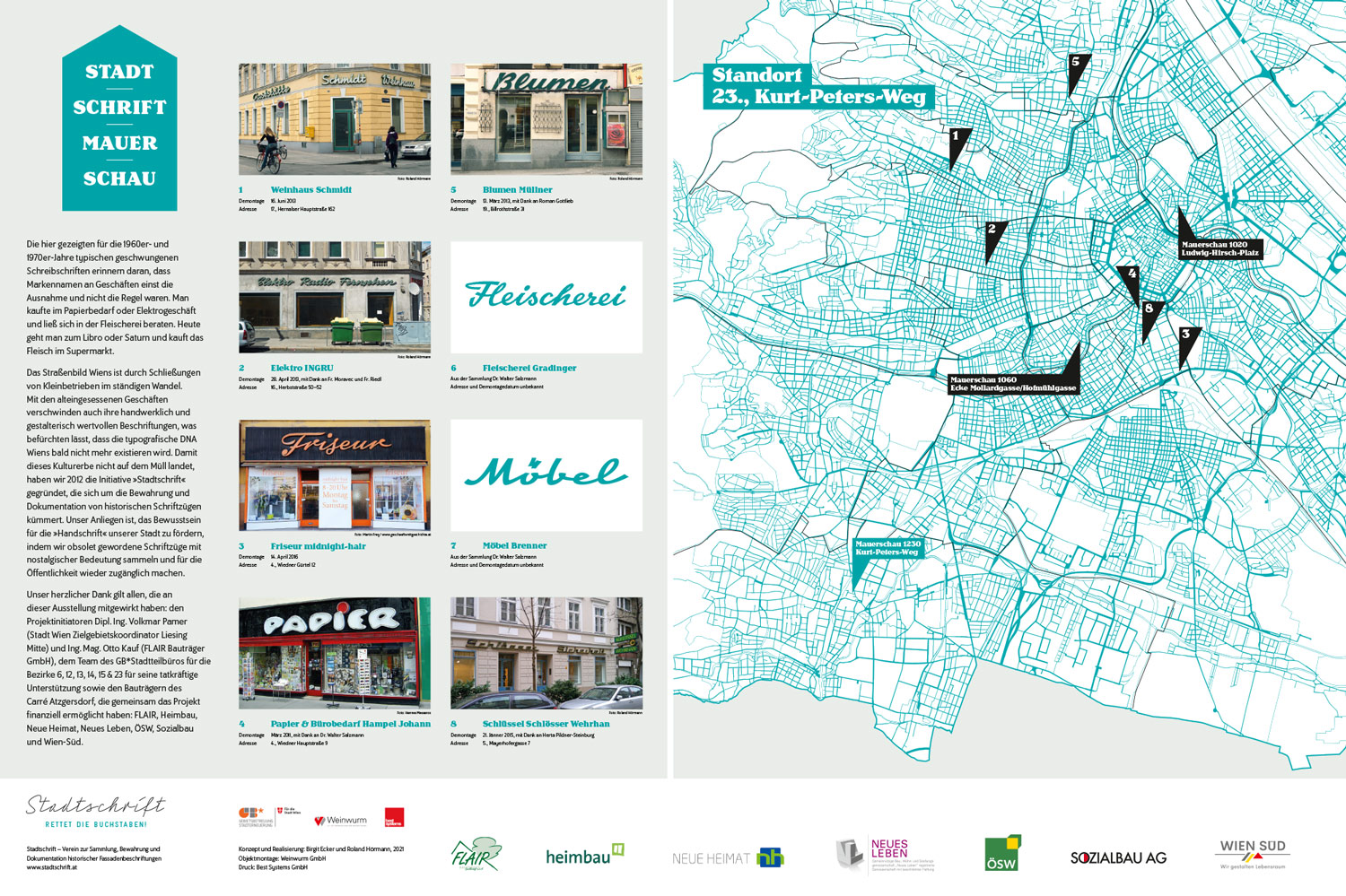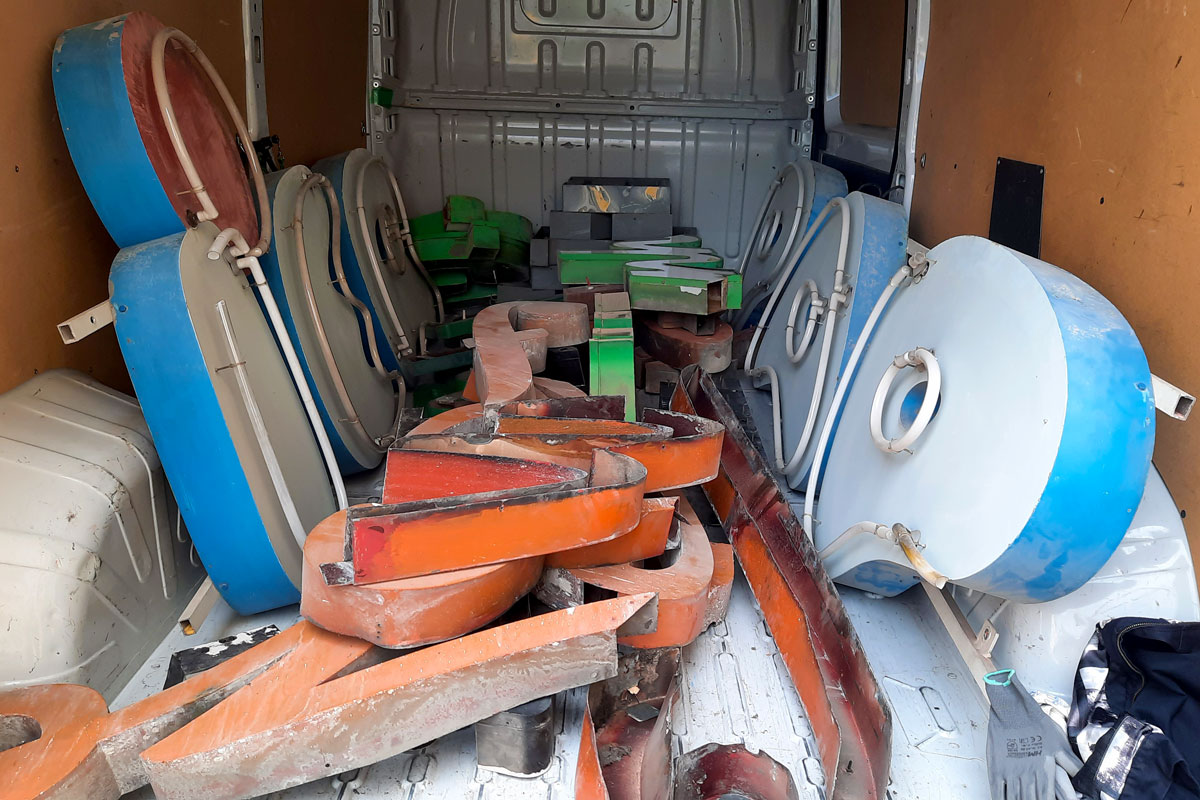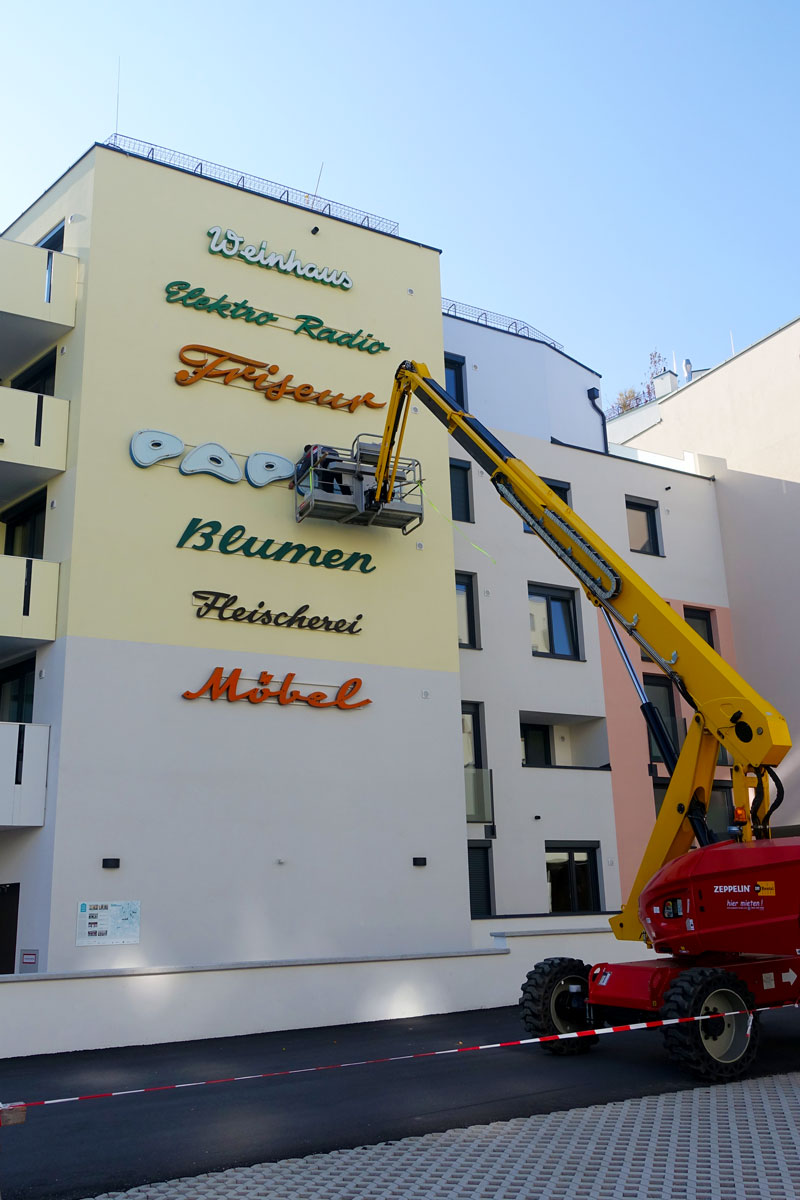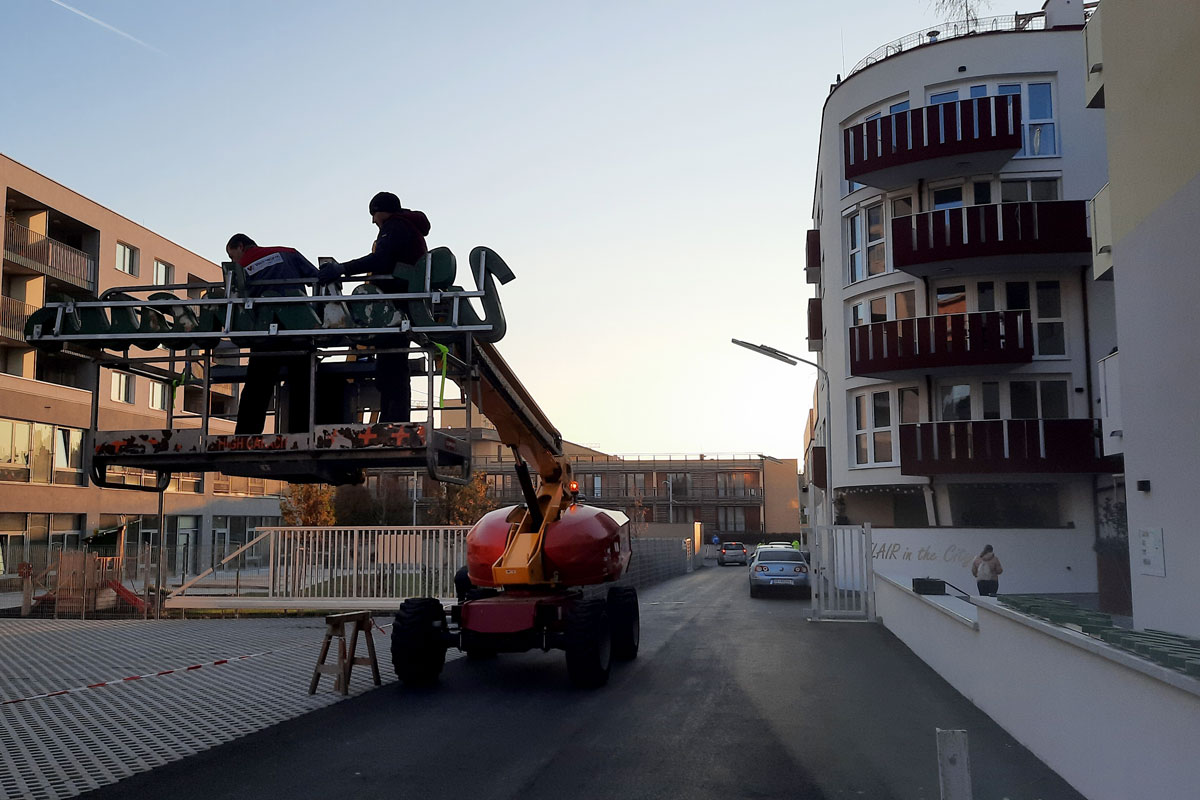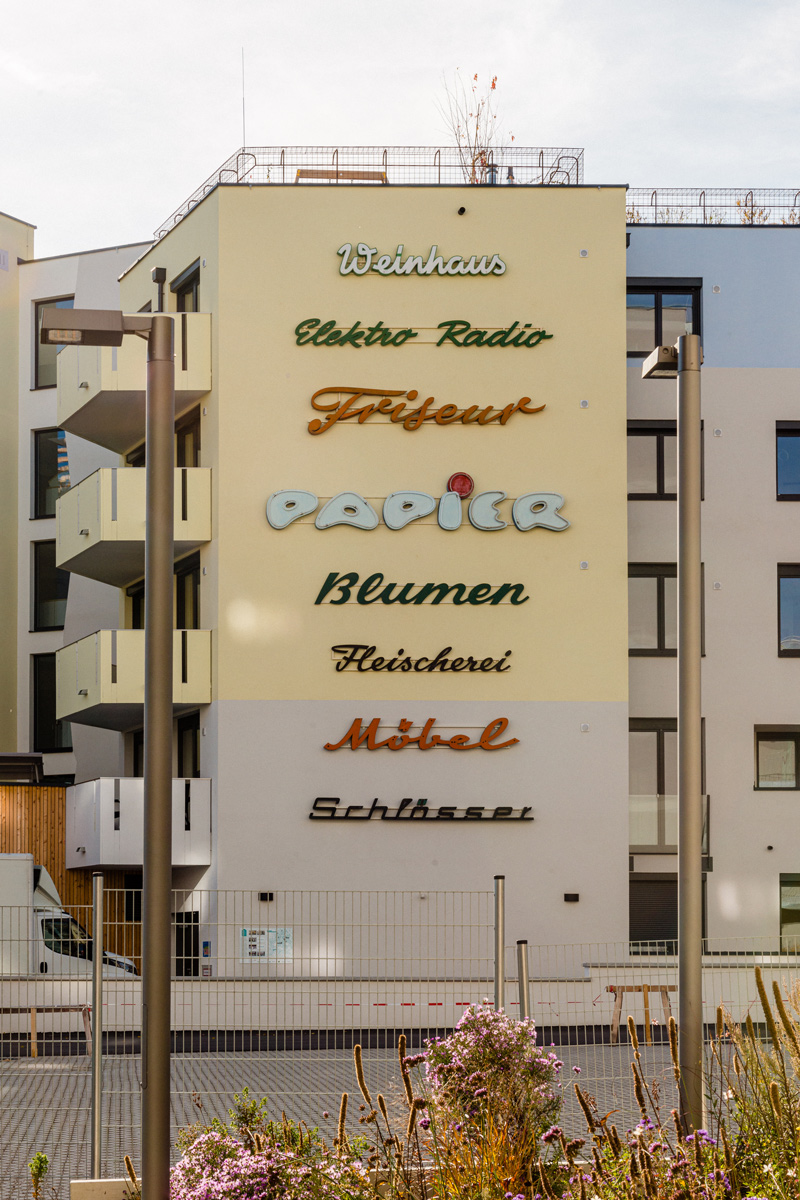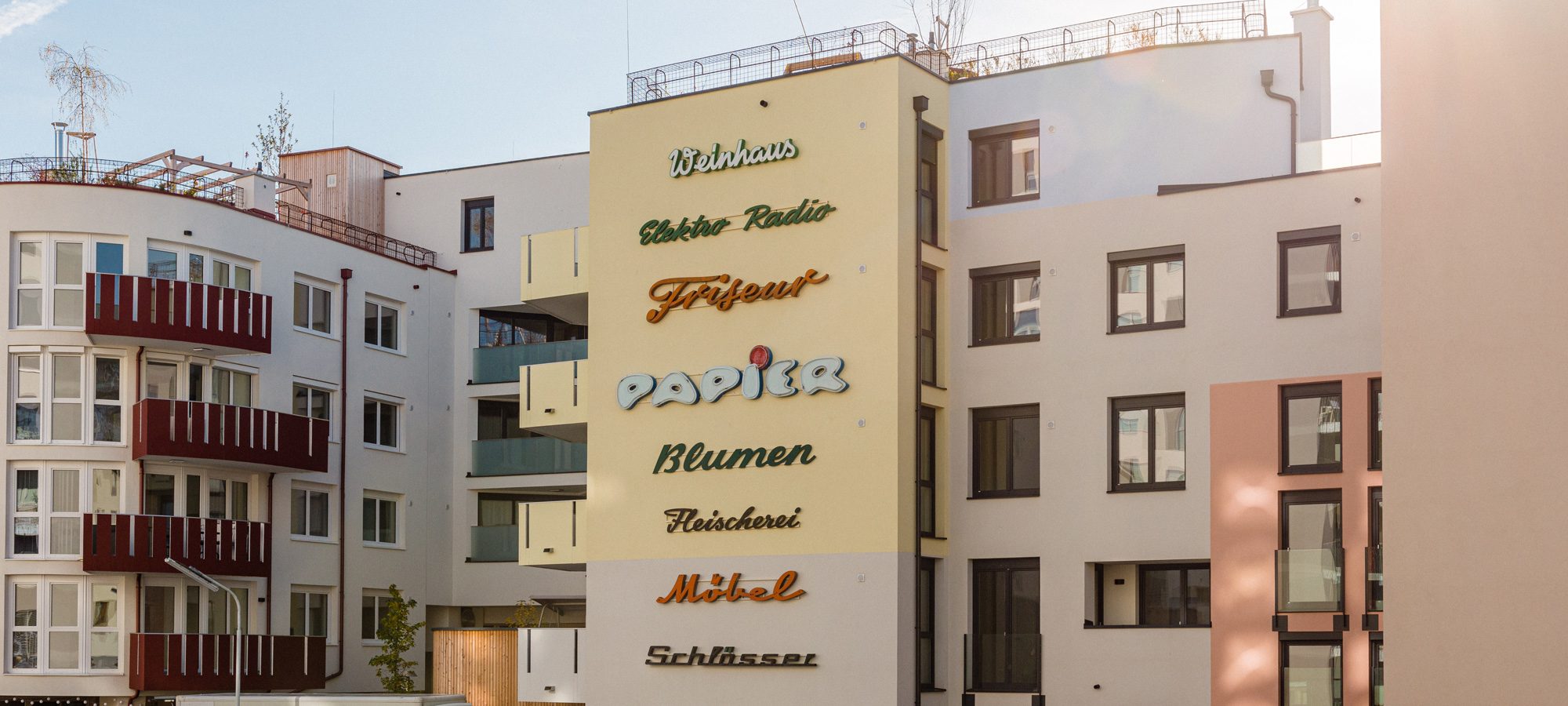
Mauerschau 1230
Carré Atzgersdorf
Kurt-Peters-Weg, 1230 Wien
seit November 2021
Im Südraum Wiens ist ein neues Stadtviertel mit rund 1500 Wohnungen, viel Grün- und Freiflächen im Entstehen – das Carré Atzgersdorf. Mit unserer vierten Mauerschau sind wir dem Reiz gefolgt, einen aufkeimenden urbanen Hotspot kulturell mitzuprägen. Die Ausstellung befindet sich am Gebäude „FLAIR in the City“, auf der vielfrequentierten FußgeherInnen-Achse vom Wohngebiet durch den Bruno-Morpurgo-Park Richtung Schnellbahnstation.
Wir haben für diesen Standort vorrangig geschwungene Schreibschriften ausgewählt, die für die 1960er- und 1970er-Jahre typisch waren. Zentrales Element ist der PAPIER-Schriftzug, der nach dem Abbau der Mauerschau 1020 Kleine Sperlgasse nun hier wieder zu Ehren kommt.